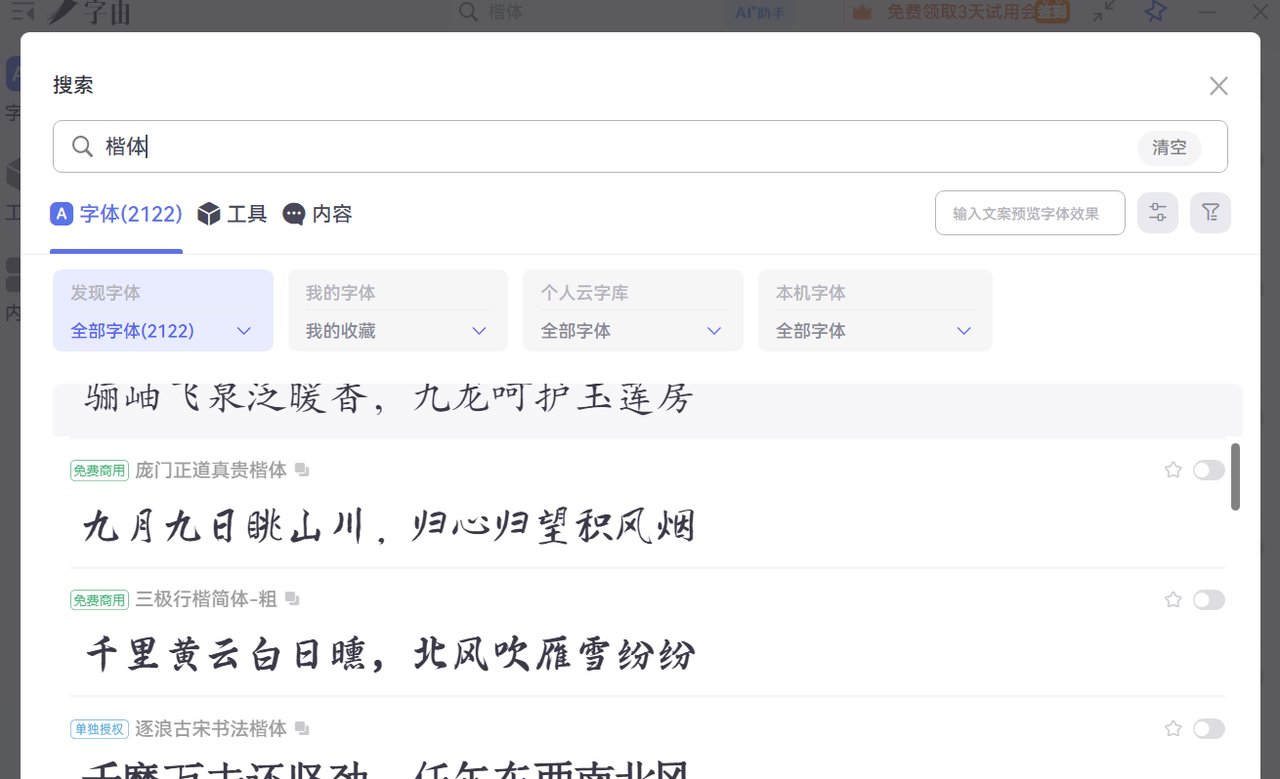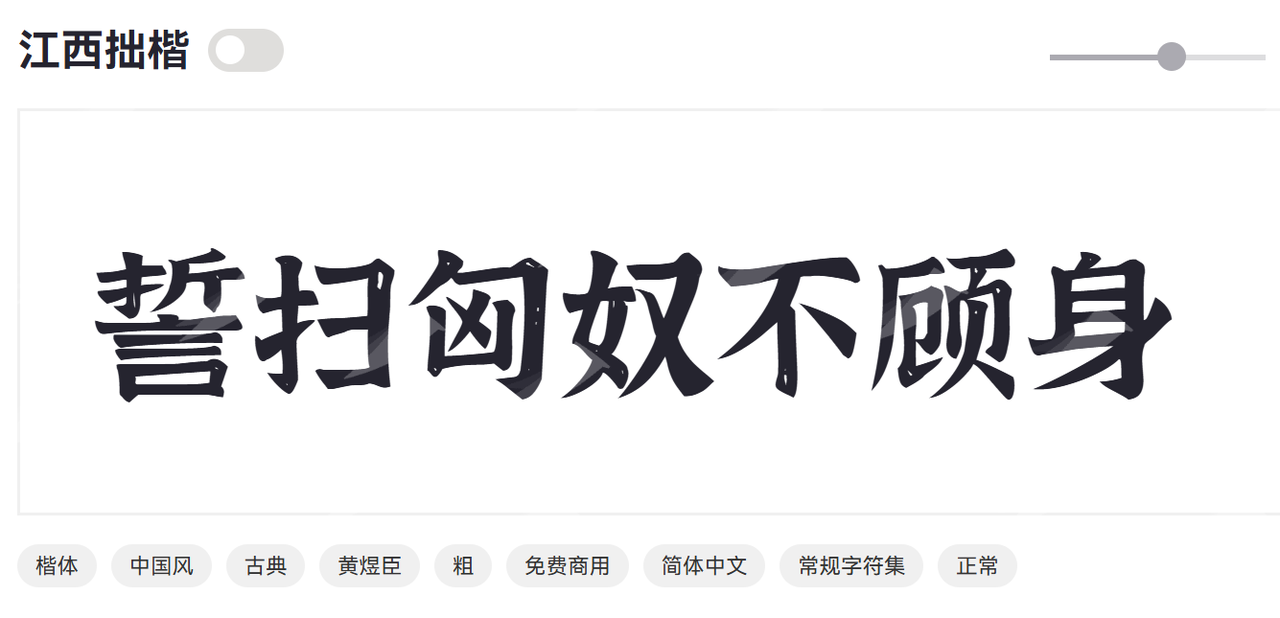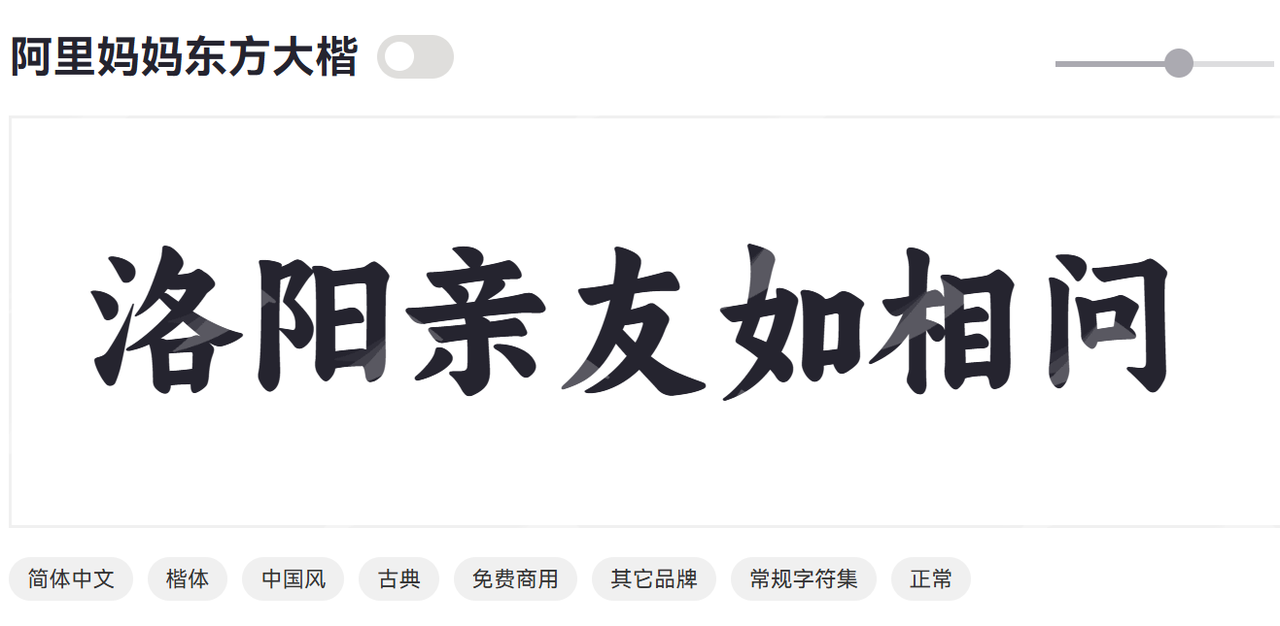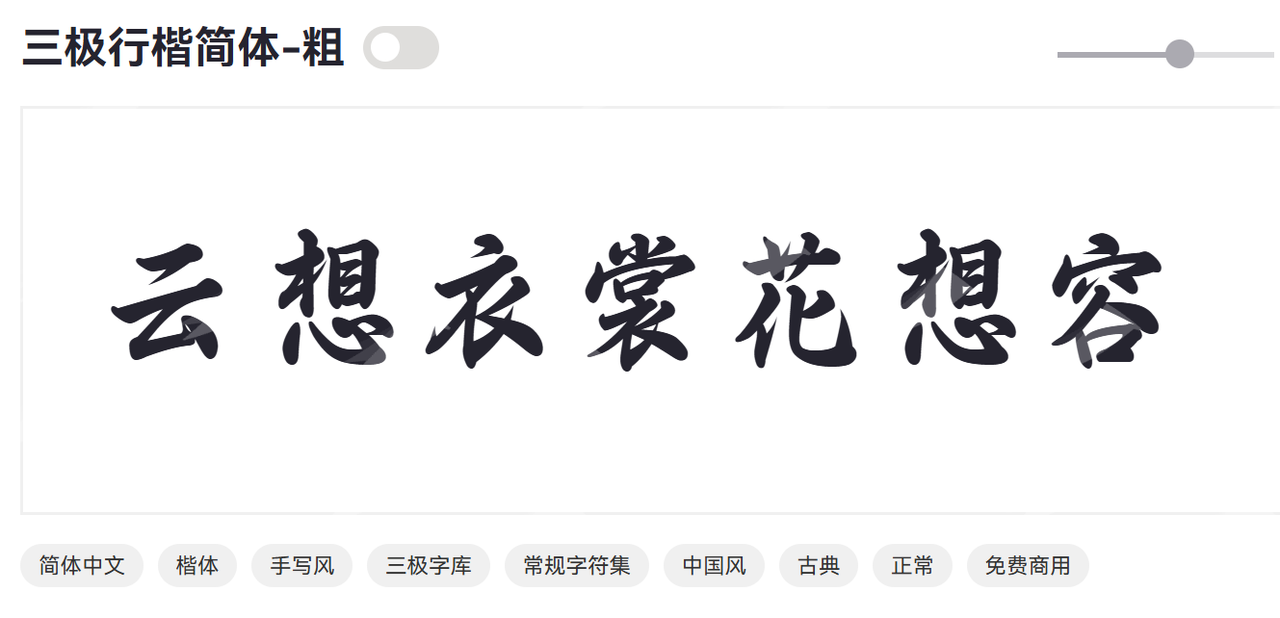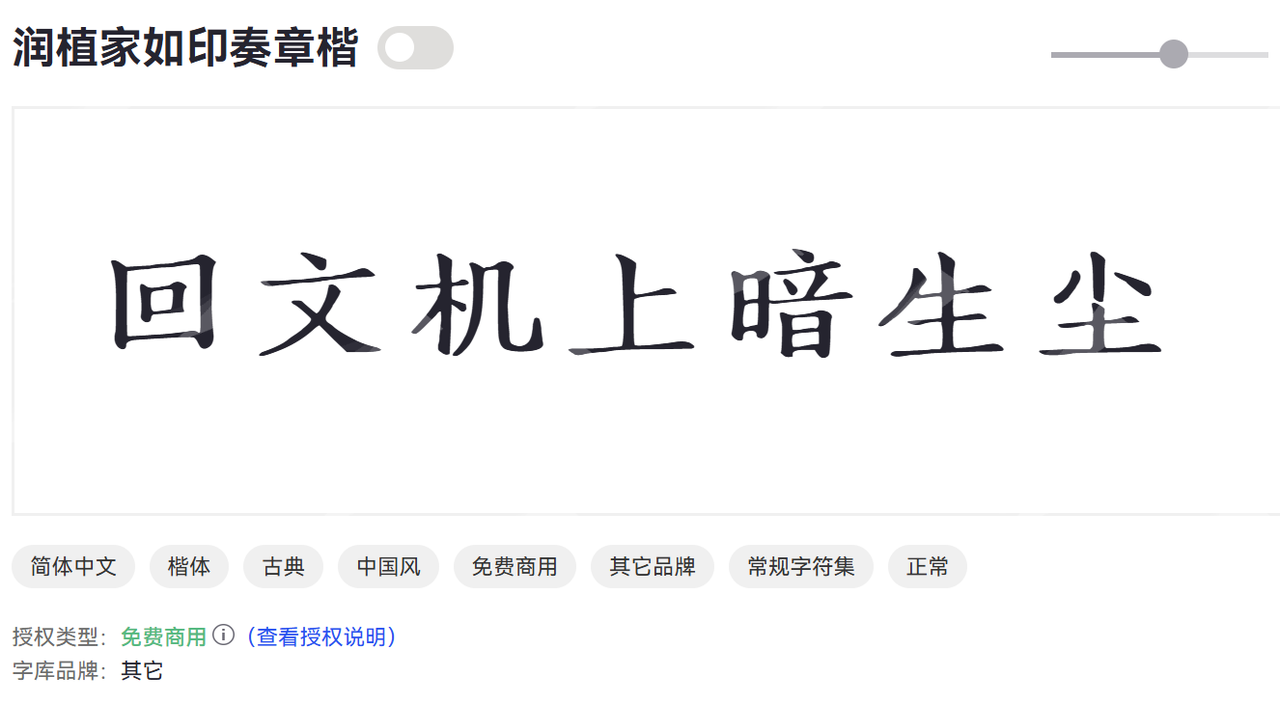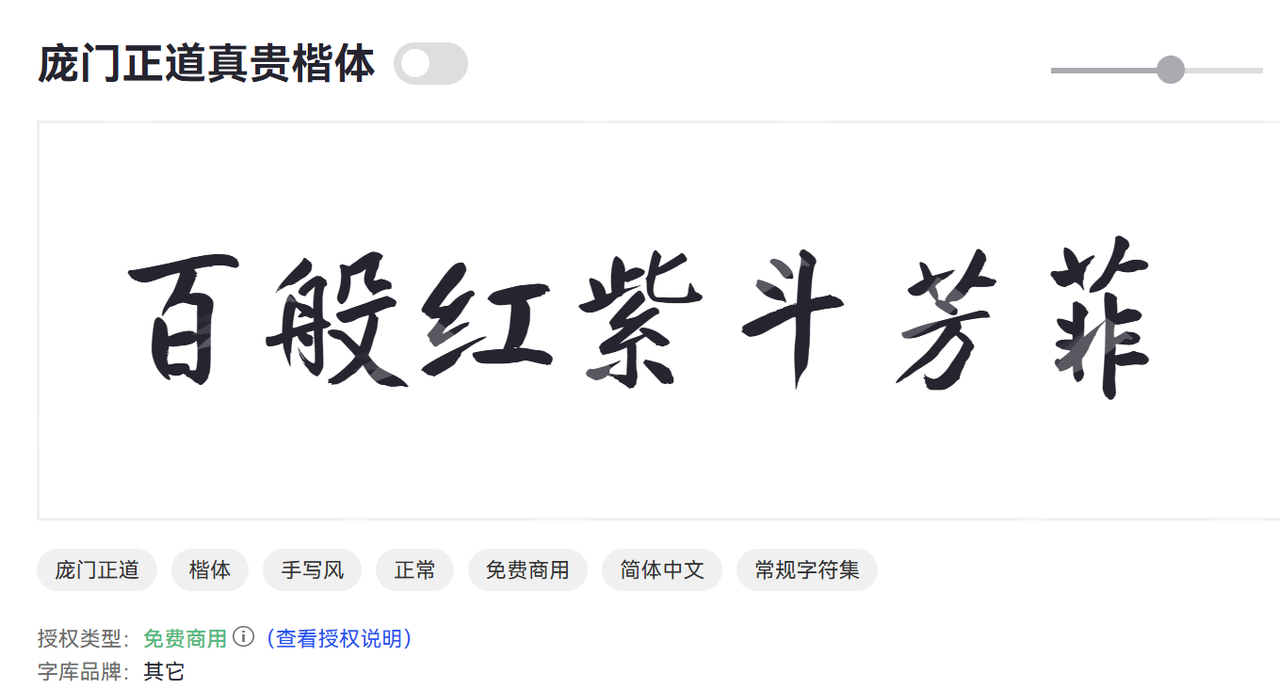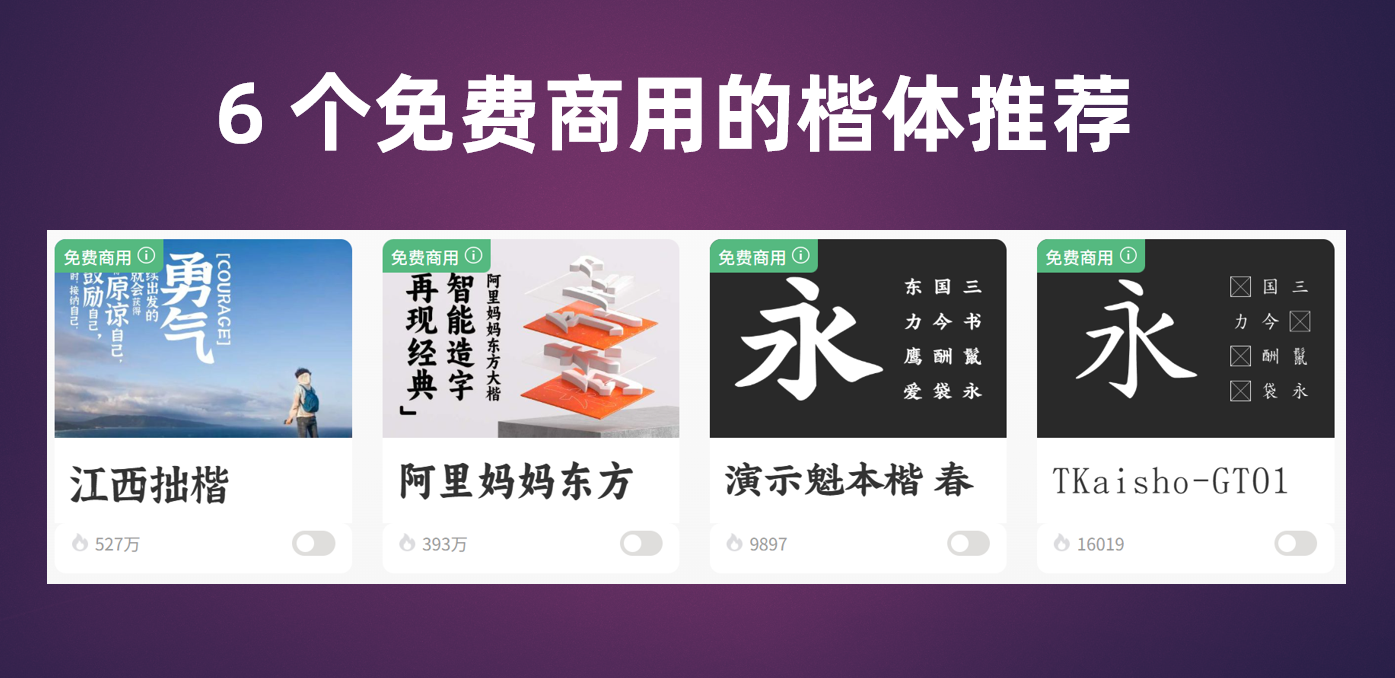
楷体字体可以商用吗?分享 6 个可以免费商用的楷体!
楷体字体可以商用吗?作为一名长期关注字体设计和使用的用户,我发现楷体在我们的日常学习、工作乃至艺术创作中都有着不可替代的地位。但是很多小伙伴在使用楷体的时候比较担心,害怕不能商用的楷体造成侵权的问题,今天,我重点给大家分享 6 个可以免费商用的楷体,帮助您可以放心在学习和工作中使用楷体字体。
一、楷体是什么字体
楷体源于汉字书法中的楷书书写风格,楷书是中国传统书法中的一种正楷字体,笔画规整、结构方正,笔锋清晰,书写工整、易辨识,是我们学习汉字书写的标准字体。
所以楷体就是借鉴了传统楷书的书写特点,它的特点是笔画有一定的起伏变化,每一笔都带有明显的笔锋,线条相对细腻且有装饰感,给人一种端庄典雅、温文尔雅的感觉。
三、6 款可以免费商用的楷体
1、江西拙楷
江西拙楷最大的特色在于其“拙”而不失灵动。笔画粗细不均,略带飞白,结构不拘泥于完美对称,仿佛出自一位饱含真情实感的书法爱好者之手。这种刻意的“不完美”赋予了字体独特的艺术魅力和真实的人文温度。
江西拙楷以其独特的朴拙之美和深厚楷书的传统文化底蕴,成为一款极具辨识度和艺术感染力的免费商用中文字体。不论是用在文化传播、品牌建设,还是创意设计,江西拙楷都非常的适合,能让您的作品提升设计感。
2、阿里妈妈东方大楷
东方大楷,作为阿里免费字体的楷体字体,也是我推荐的老朋友了,阿里妈妈东方大楷拥有传统楷书的方正结构、横平竖直的笔画特点,字体骨架严谨,笔力雄厚。整体风格沉稳、大气,给人以庄重、权威之感。
阿里妈妈东方大楷凭借其楷书的庄重典雅、浓郁的东方神韵以及强烈的视觉冲击力,比较适合在电商营销、品牌广告、国潮设计和文化传播领域进行使用,可以帮我们把信息表达的更加清晰,提升一些视觉传播上的效果。
3、三极行楷简体
三极行楷简体是一款结合行书和楷书的字体,最大的特点是其笔画之间的自然连带,既有行书的洒脱飘逸,又保留了楷书的结构骨架,使得字体整体看起来流畅但又正式,就像班里字写的好看同学的字迹,真的很帅。
三极行楷简体是一款集流畅优雅、人文气息与实用易读于一身的中文字体。它以其独特的行楷风格,完美平衡了书法艺术性和现代设计需求,在品牌塑造、文化传播、创意设计等场景都是非常不错的选择。
4、庞门正道真贵楷体
庞门正道真贵楷体是一款由知名设计平台庞门正道团队精心打造的中文字体。它以楷体为基础,融入了现代审美和独特的设计理念,旨在传达一种“真正宝贵、值得信赖”的视觉感受。
庞门正道真贵楷体是一款集端庄稳重、精致考究与现代力量感于一身的中文字体。它以其独特的楷体风格,完美平衡了传统美学与现代设计需求,对于企业形象塑造、商业广告传播、文化内容等场景比较适合。
5、润植家如印奏章楷
润植家如印奏章楷是一款独具匠心的中文字体,其命名精准概括了自身特色:**“如印”喻示其带有印章刻凿的古朴韵味和方正之美;“奏章”则点明其庄重、正式,蕴含古代官方文书的厚重感;而“楷”**则表明其以楷书为基础结构。
润植家如印奏章楷以其方正稳健、庄重典雅、历史厚重的独特气质,成为表现中国传统文化、国风美学、高端品牌形象以及正式庄严主题的理想选择。无论是平面设计、品牌塑造还是数字媒体,这款字体都能可以和您的作品完美适配。
6、寒蝉正楷体
寒蝉正楷体作为一款正楷字体,它严格遵循楷书的字形结构,重心平稳,笔画规范,确保了极佳的阅读性和辨识度。即使在小字号下,也能保持清晰的字骨。
寒蝉正楷体是一款将传统楷书的端正规范与现代设计的清雅纤细完美融合的中文字体。如果你想做一些艺术、高端品牌、文化传播相关的创作,那么寒蝉正楷体非常合适,可以在视觉上表达的精致和高品位。
四、适合楷体的一些使用场景
• 教育和教学
楷体是学习汉字书写的标准字体,广泛用于教科书、练字本和汉字教学资料中,帮助学生规范书写。
• 正式文档与公文
由于楷体端庄规范,常被用于正式文件、证书、奖状等正式场合,展现严肃和权威。
• 文化宣传和书法艺术
楷体带有浓厚的书法韵味,适合文化类宣传材料、古籍排版、书法作品数字化展示等。
• 品牌设计
一些文化品牌、传统行业、茶叶包装、古典风格的产品都会采用楷体,以传达传统与品质感。
• 创意设计与标题
楷体的艺术美感使它成为设计师在封面、海报、广告标题等需要突出文化底蕴时的首选。
五、总结
如果你想要一款既有文化底蕴又适合正式场合的中文字体,楷体绝对是不二之选。它的端庄美观,既适合学习教育,也适合文化品牌和正式文件。但是并不是每一款楷体都可以免费商用的,大家可以选择本文给大家分享的 6 款免费商用的楷体。快速获取方式可以通过字由客户端获取这 6 款免费商用的楷体。